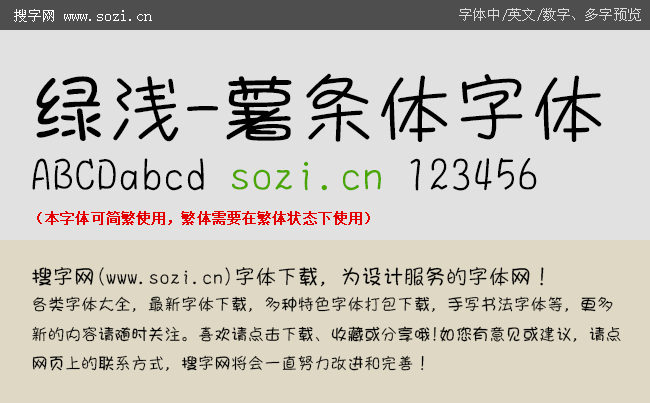
薯?xiàng)l體字體
薯?xiàng)l體字體是一款搜字網(wǎng)提供中文字體下載,薯?xiàng)l體字體帶上了pop字體的設(shè)計(jì)風(fēng)格,可以用于可愛設(shè)計(jì)方面的字體,如廣告設(shè)計(jì)字體、網(wǎng)頁設(shè)計(jì)字體、包裝設(shè)計(jì)字體、 屏幕顯示字體等。